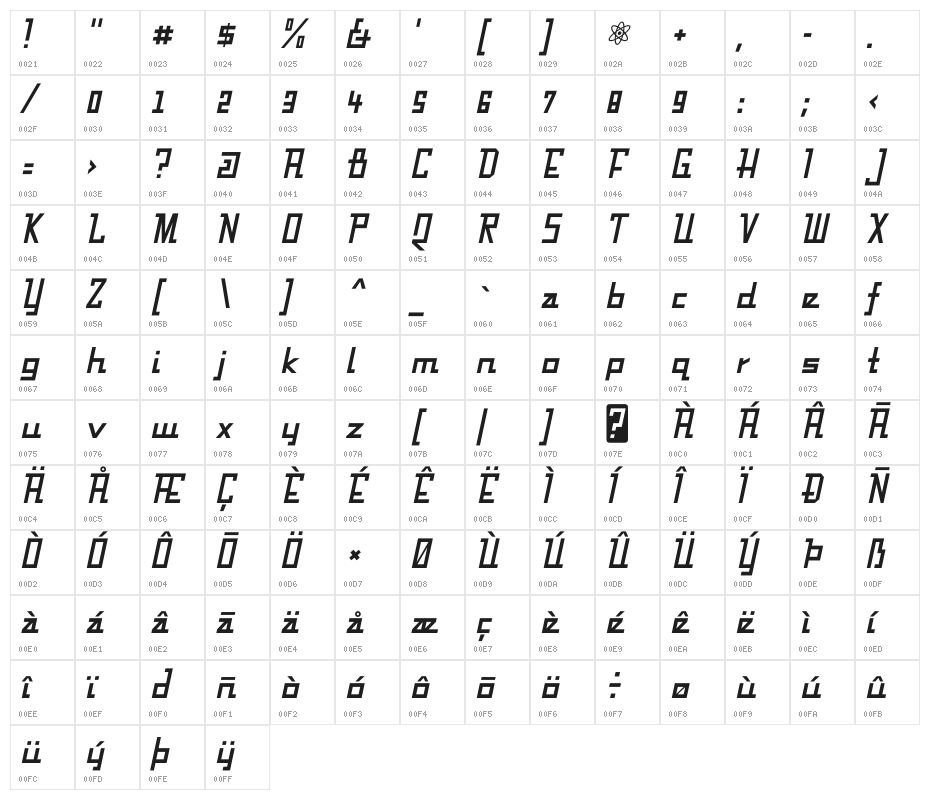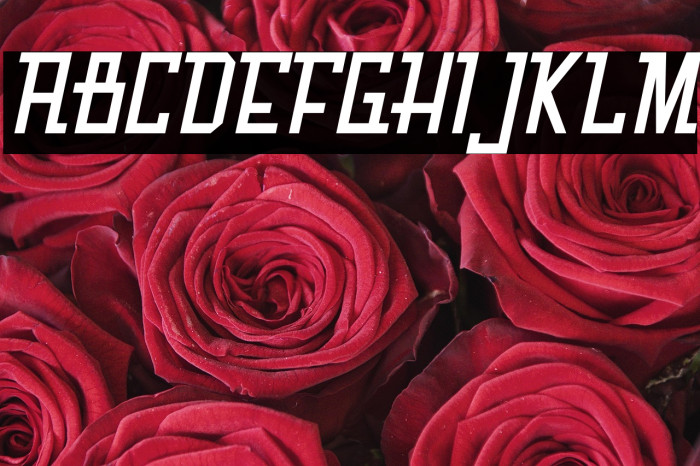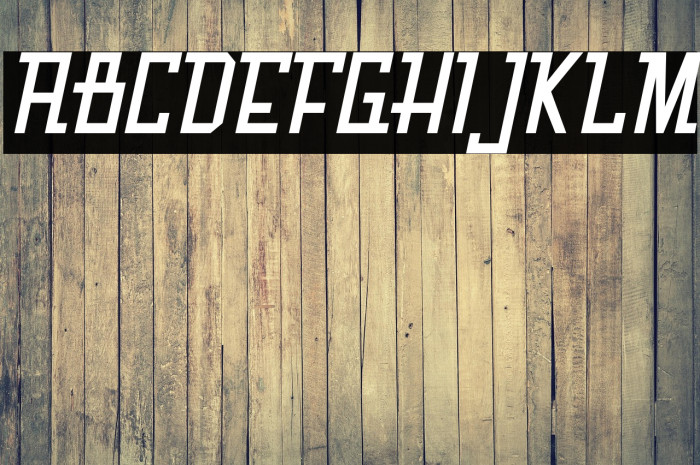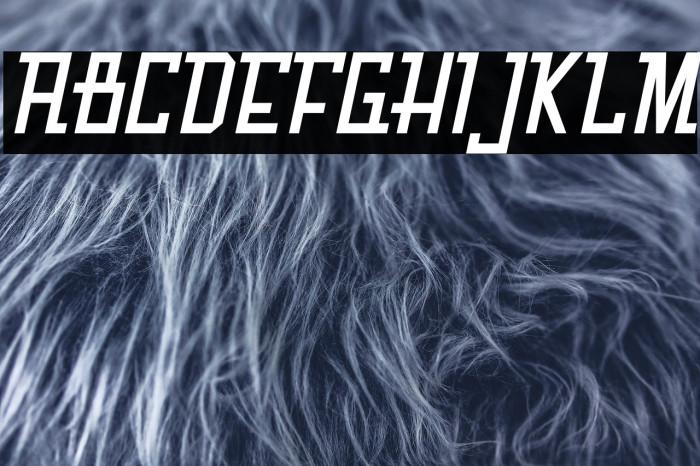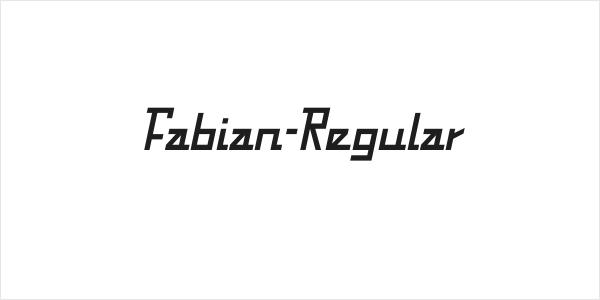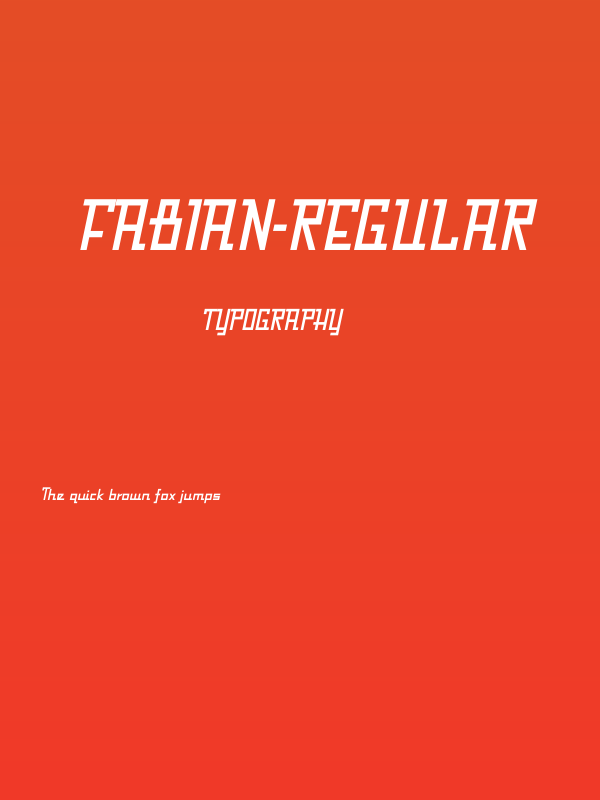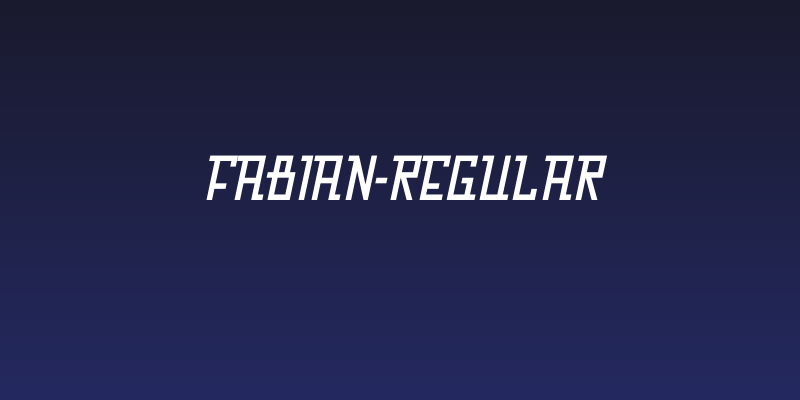
Fabian-Regular Font
✎ Thick
| Kategorien | Thick |
| Anwendungsfall | Headlines, Logos, Branding |
| Vorgeschlagene Projekte | Ideal for branding, advertising, and digital media projects that require a modern and bold aesthetic. |